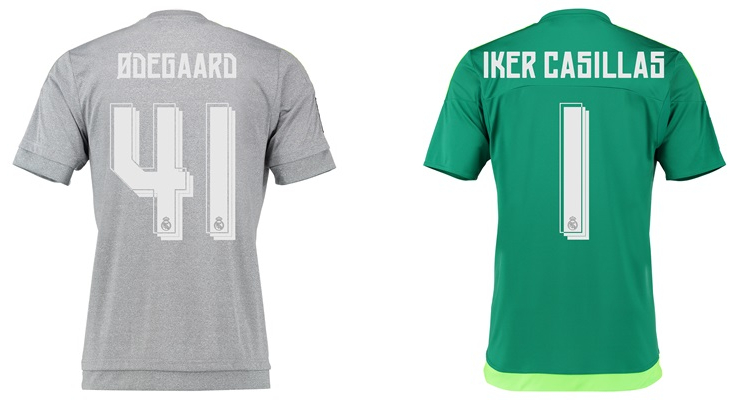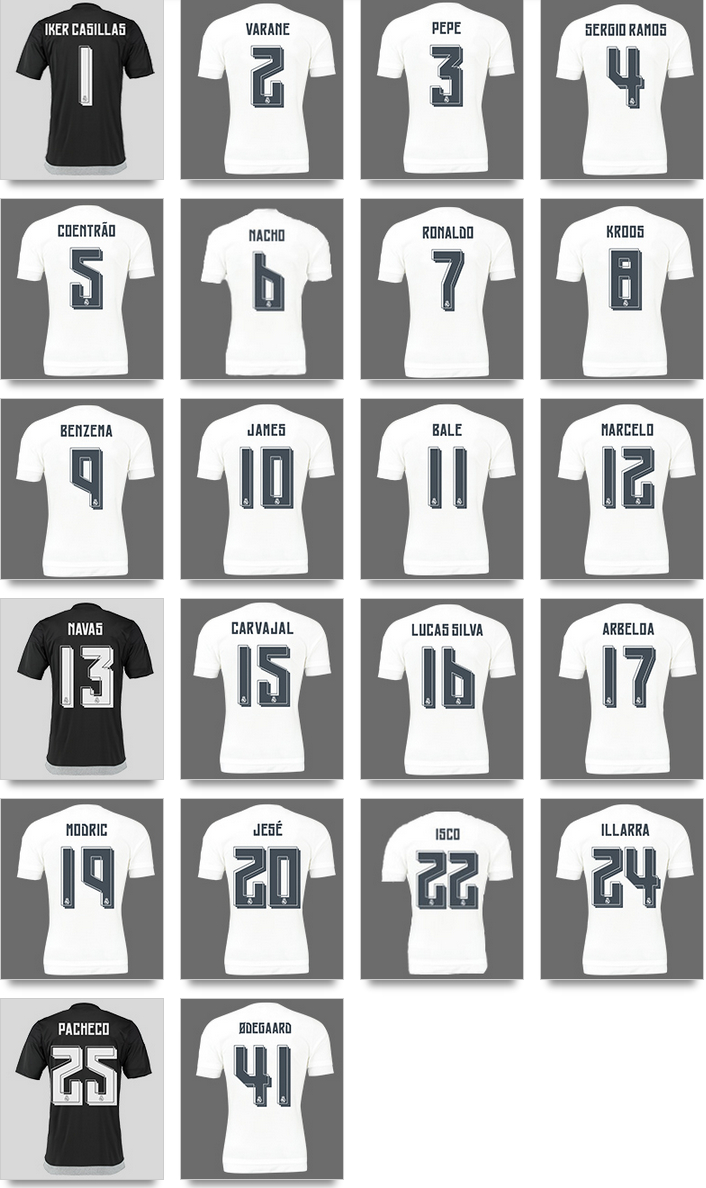
レアル・マドリーは、先日2015-16シーズンに向けた新たなユニフォームを発表した。
すでにオーダー受付も始まっている、この新ユニのフォントがなかなか面白い感じになっている。
角ばったデザインで、特徴的なのが背番号。3つのレイヤーが重ねられていて、立体的に見える。グレーのアウェイユニとグリーンのGKユニはこんな感じ。
また、公式オンラインショップでも背番号は既に来季仕様になっており、イスコは22番、ナチョは6番に。なお、イスコがつけていた23番はポルトからやってきたブラジル代表右SB、ダニーロがつける。